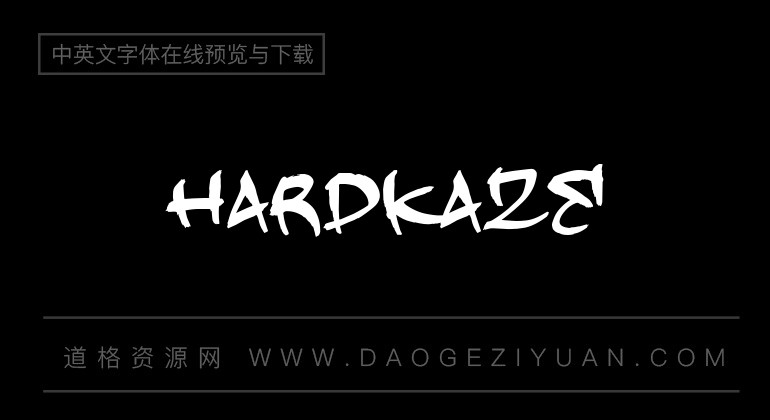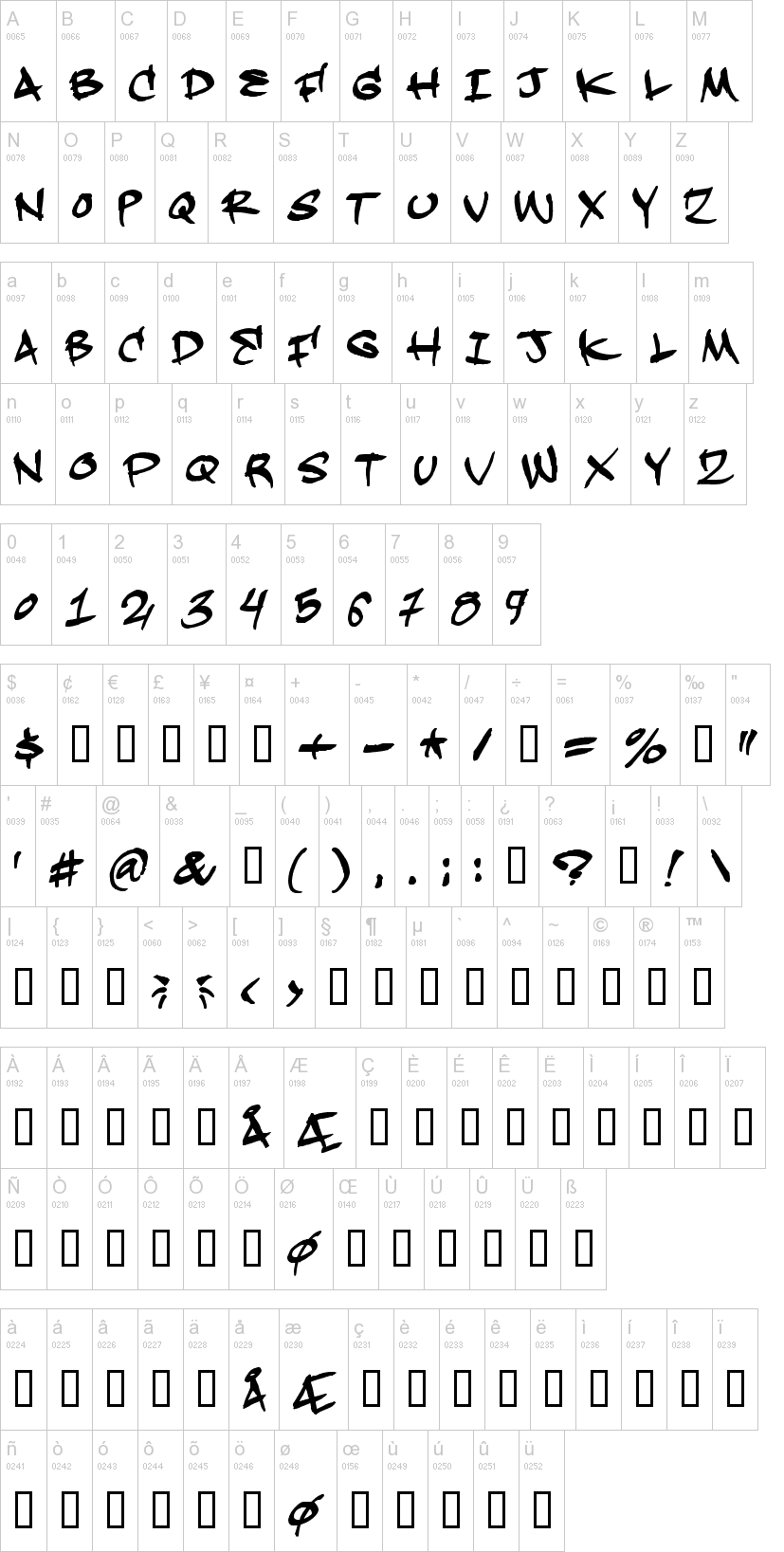
Hardkaze
Hardkaze 字体是一款由 Japanese designer 设计的日本风格的字体,它具有清新、简洁、抒情、活泼、细腻的特点,适合用于报纸、杂志、海报、书籍、网页等各种印刷品的设计。它让人们感受到日本传统文化的魅力,能够更好地传达出设计师的想法。
Hardkaze是一款非常不错的手写艺术字体,具有很好的视觉感,适合于文化类的宣传设计、商业类品牌的广告和产品包装设计以及个性化文字排版等较多场景。
Hardkaze字符映射图